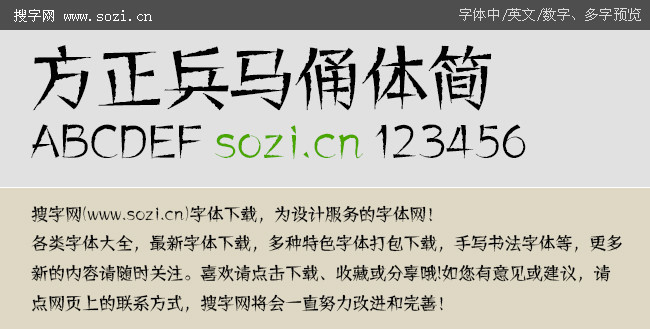
方正兵馬俑體簡(jiǎn)
搜字網(wǎng)提供一款方正兵馬俑體簡(jiǎn)中文字體下載,方正兵馬俑體傳達(dá)出不同的價(jià)值觀訴求,不同的審美取向,不同的人文特征。 是一款描述歷史、詮釋滄桑、抱樸守靜、彰顯耐力的排版文字。 同時(shí)也是古今語(yǔ)境的接引者。能夠適用于藝術(shù)設(shè)計(jì)、包裝印刷、圖形設(shè)計(jì)等應(yīng)用。